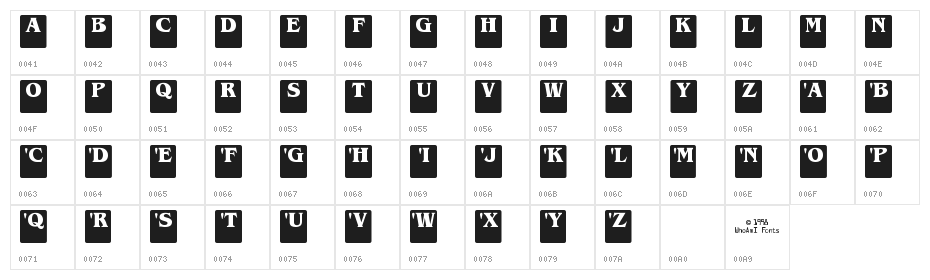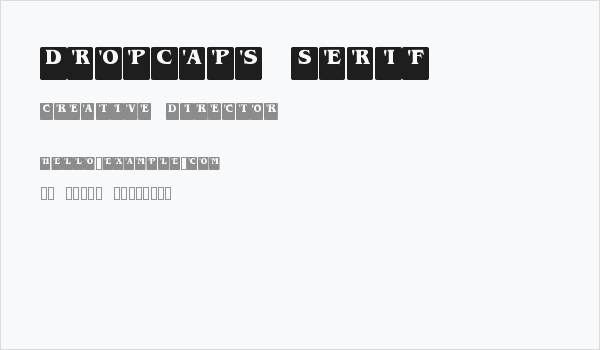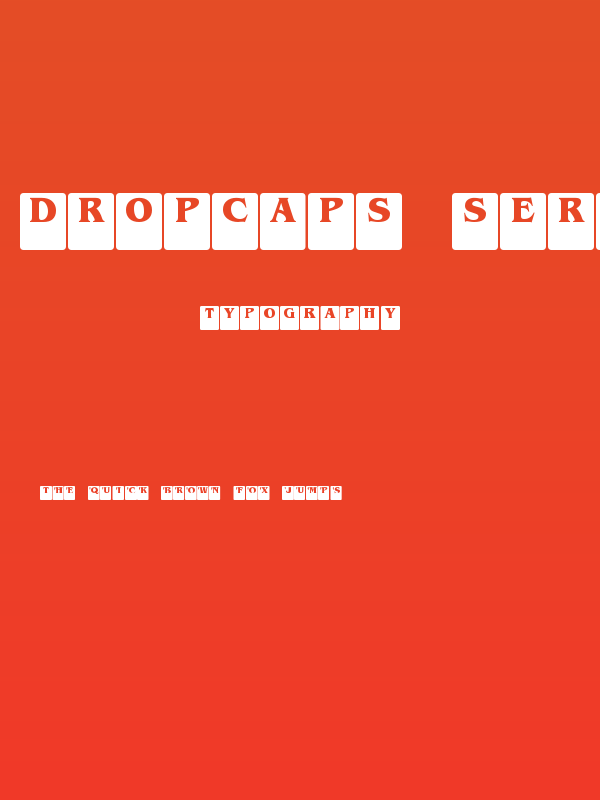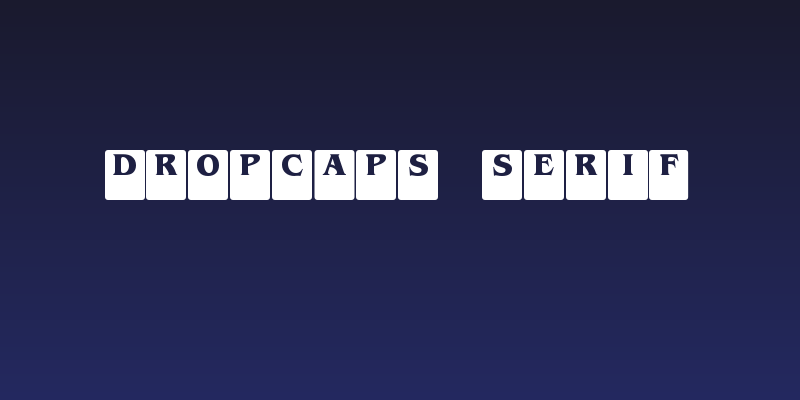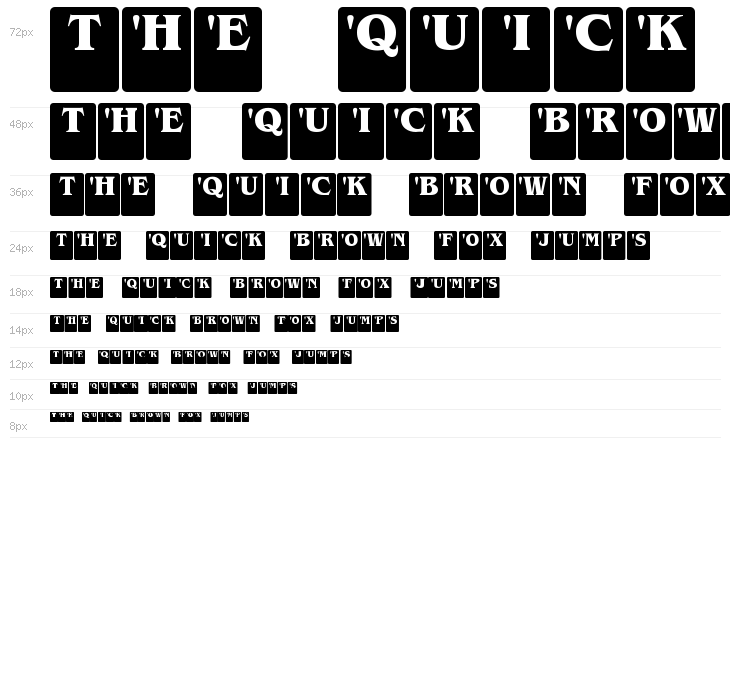
DropCaps Serif Font
| Caso d'uso | Headlines |
| Progetti proposti | Perfect for book covers, posters, and any design requiring a strong, classic impact. |